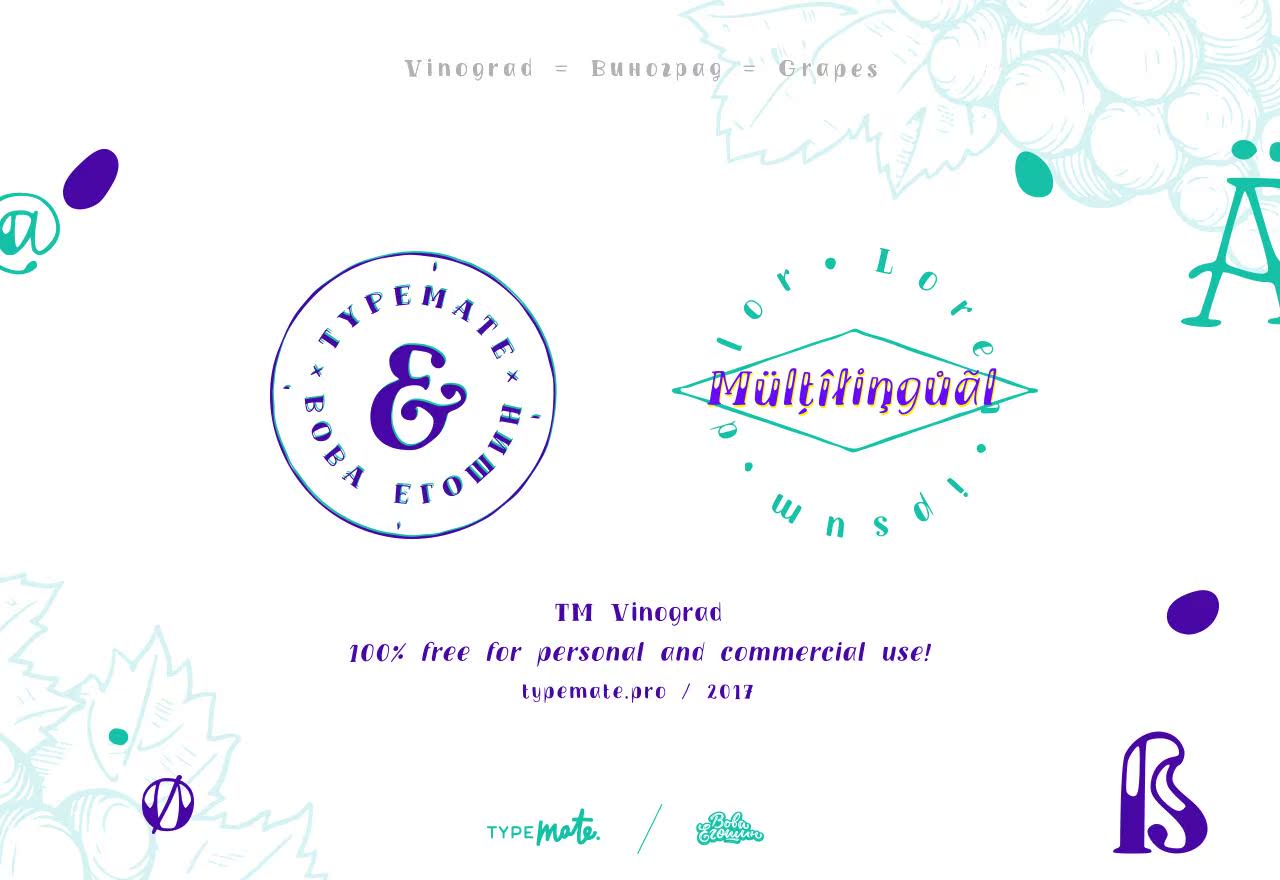
TMVINOGRADFREEHANDRITENTypeFaces是一组显示字体,非常具体和对比!这些字体适用于不同的设计目的。结合不同的风格,为标题、徽标、包装创建一个完美的设计。它非常适合儿童书籍、杂志和T恤衫!此外,它还与扩展的西里尔语和拉丁语混合在一起!2样式/2说明/600+字形100%免费供个人或商业使用!